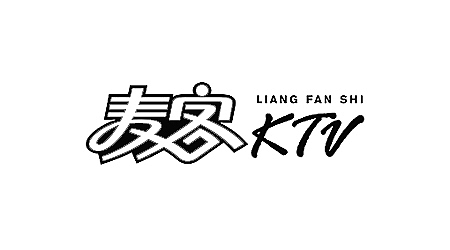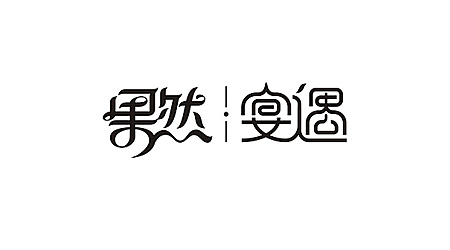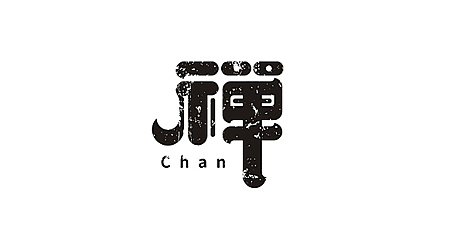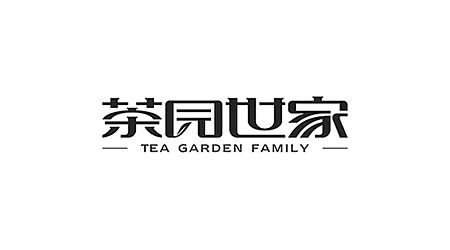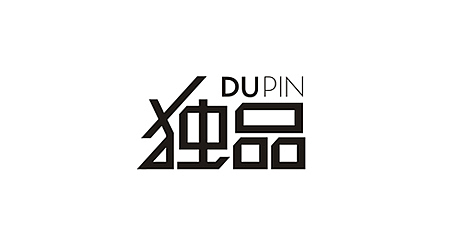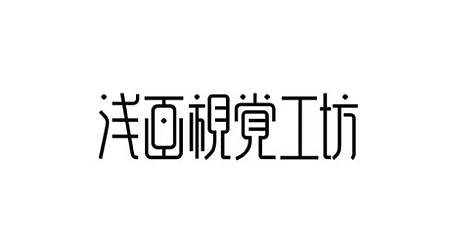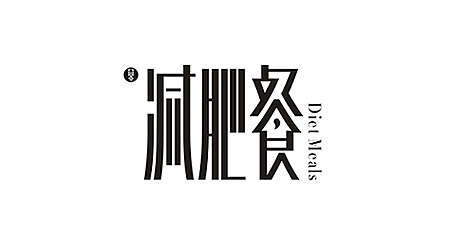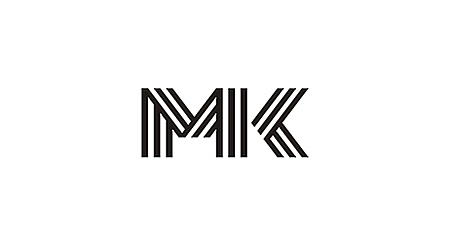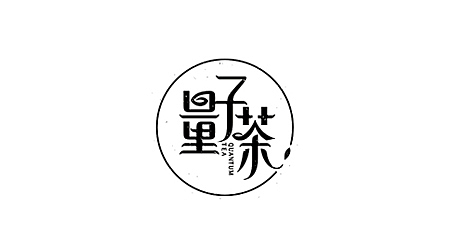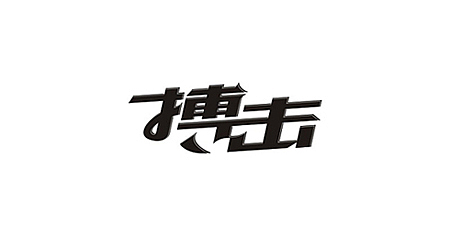
李 鑫
籍貫:湖南岳陽
品牌設計師 / 字體設計師 / 藝術指導 / 尖荷系全國實戰導師
藝酷推選設計師 / B-young 設計機構首席執導
十年前從農村走向城市,本着不與世俗同流不能被社會節奏感所同化的態度,對設計藝術的堅持自學自悟,品牌字體是我所堅持的一個點,每一個字體都是一個具備思想的生物體,有樣貌、有靈魂,無論哪個國度,都能將不同的字形呈現出不一樣的視覺姿態和內在含義。
以下作品均为近一二年的可公开的作品,喜欢黑白稿,因为黑稿最能看出美感和不足,谢谢!